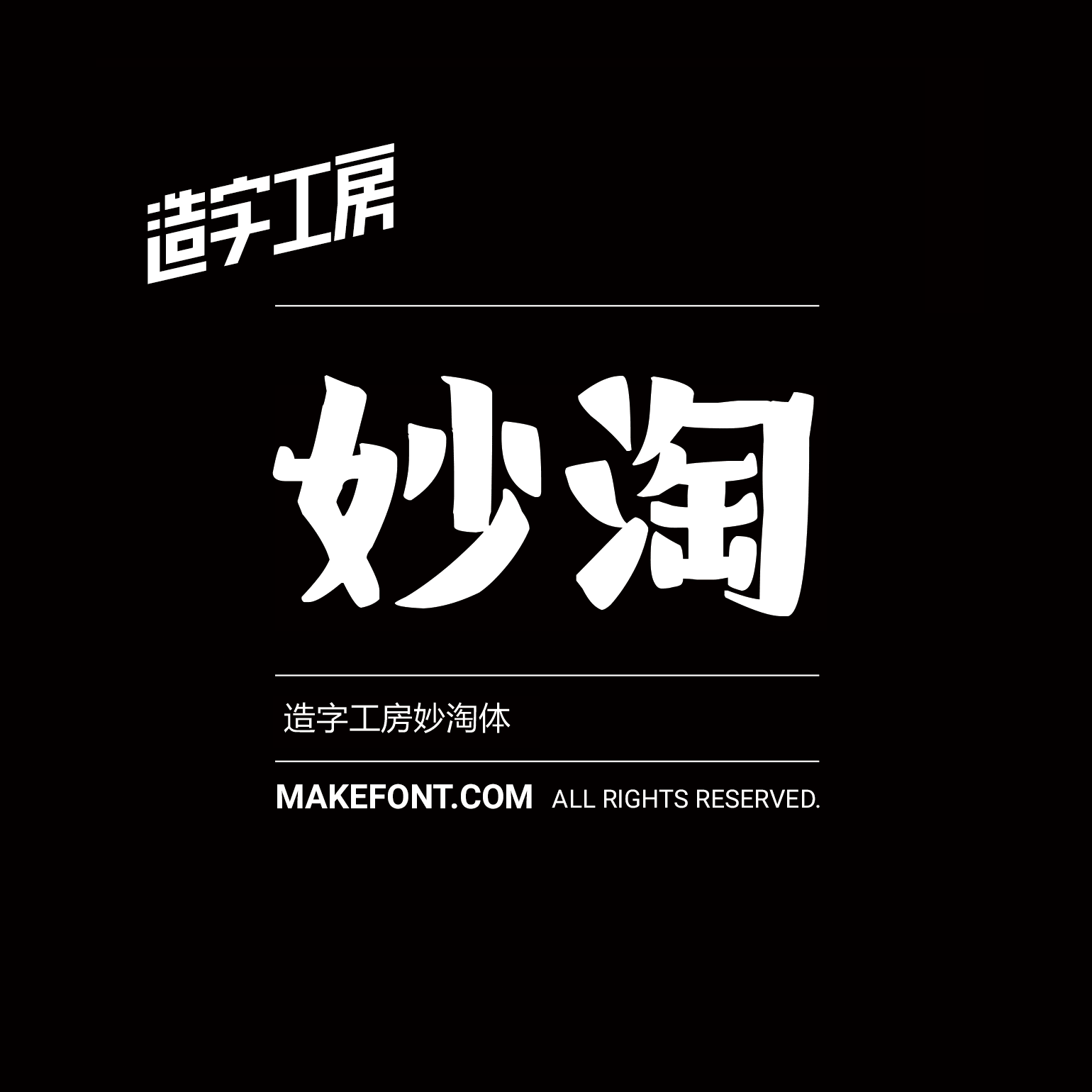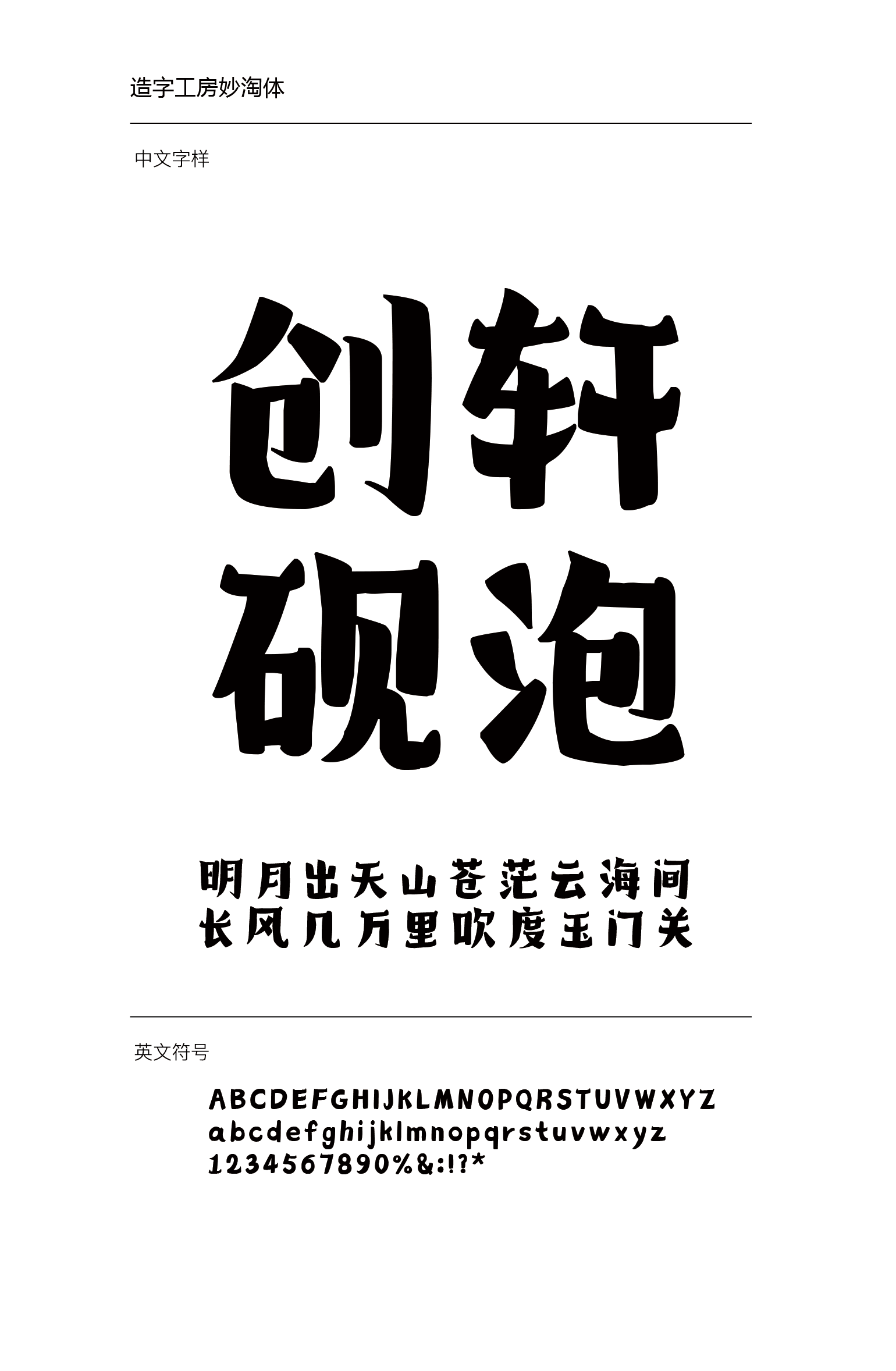
造字工房妙淘体设计说明
造字工房妙淘体,用笔锋正力劲,峻韧峭拔,力顶千钧;其体势紧密,间架严谨,风骨挺拔。其整体风格静穆而深远,具有极强的视觉冲击力。适用于艺术作品及个性品牌设计推广等环境。本字体为简体字库,采用OpenType/CID格式,Adobe-GB1-5编码。基于中华人民共和国GB2312-80字符集标准,另按需添加101个汉字。共收容字数6864CJK汉字,ASCII常用字符100个。